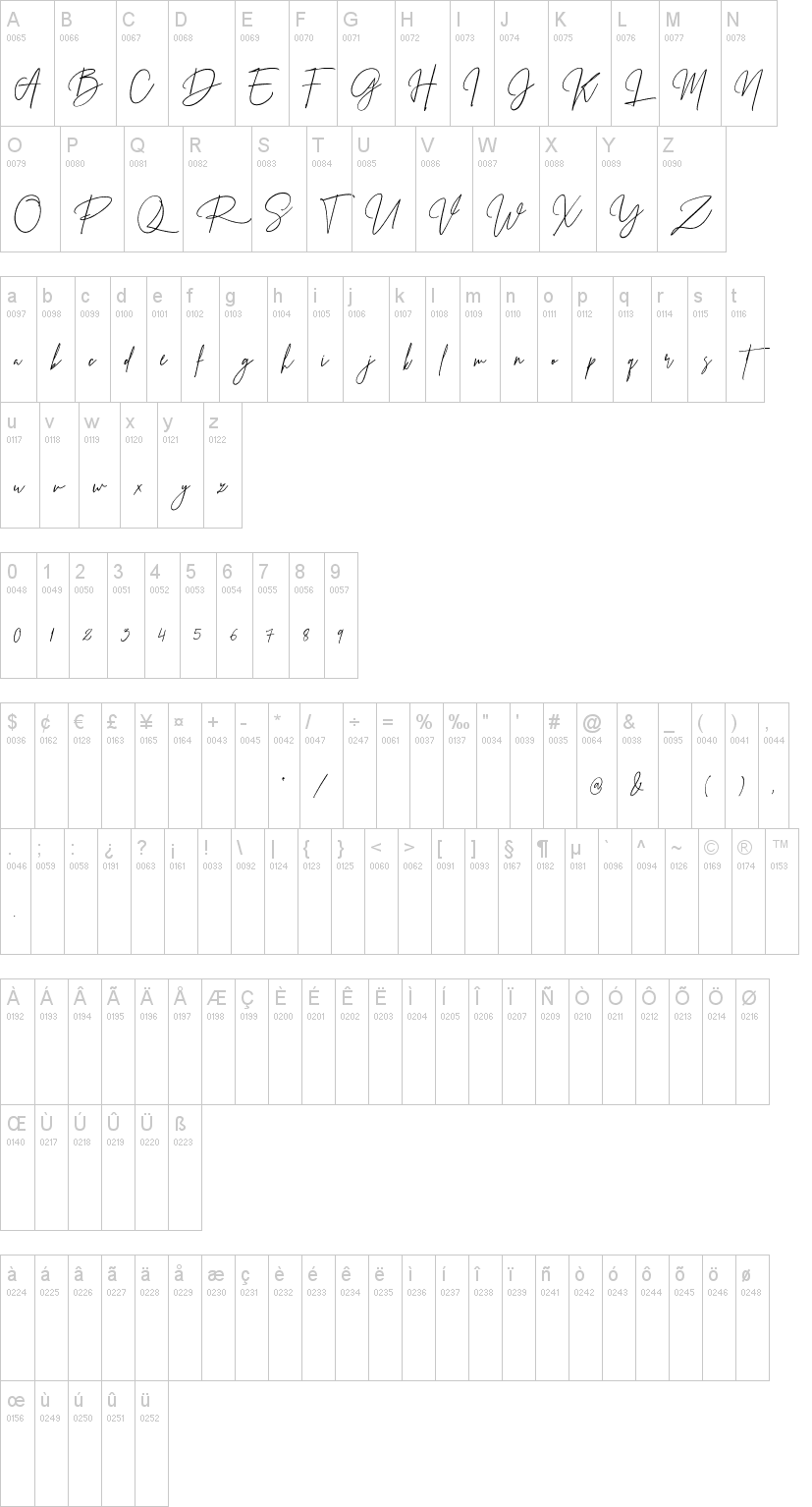
Prestige Signature Script 是一款脚本字体,由著名的字体设计师 John Hudson 创作,由 Monotype 的 Fonts.com 推出。它是一款优雅的脚本字体,可以添加一种优雅而精致的气质,搭配精美的曲线和流线型,可以为您的文字添加活力,令人印象深刻。它可以用于任何类型的文字,包括标题、正文、封面、卡片、海报等等,从而让文字更加生动有趣。内容介绍
Prestige Signature Script是一款非常不错的手写艺术字体,具有很好的视觉感,适合于文化类的宣传设计、商业类品牌的广告和产品包装设计以及个性化文字排版等较多场景。